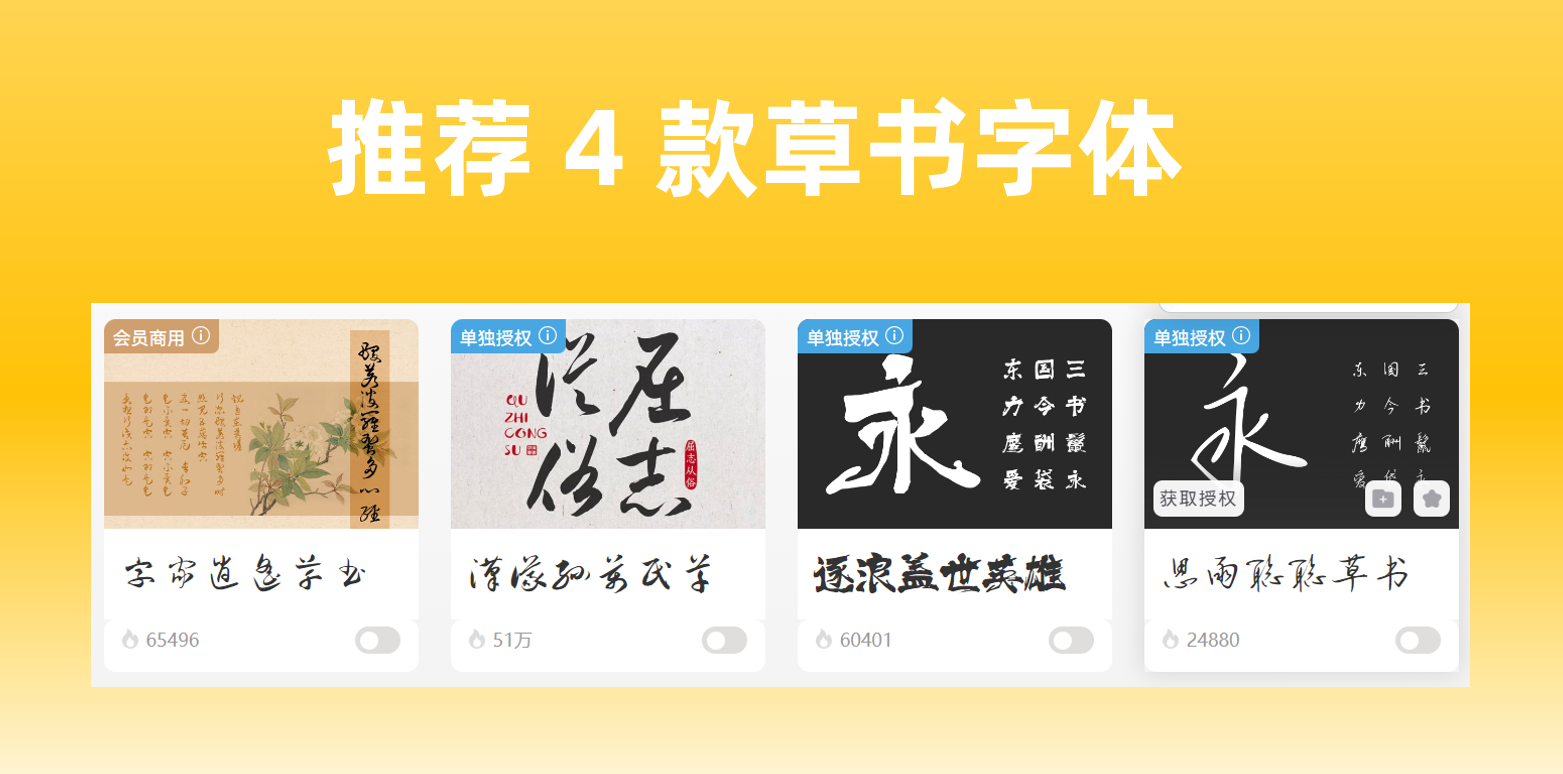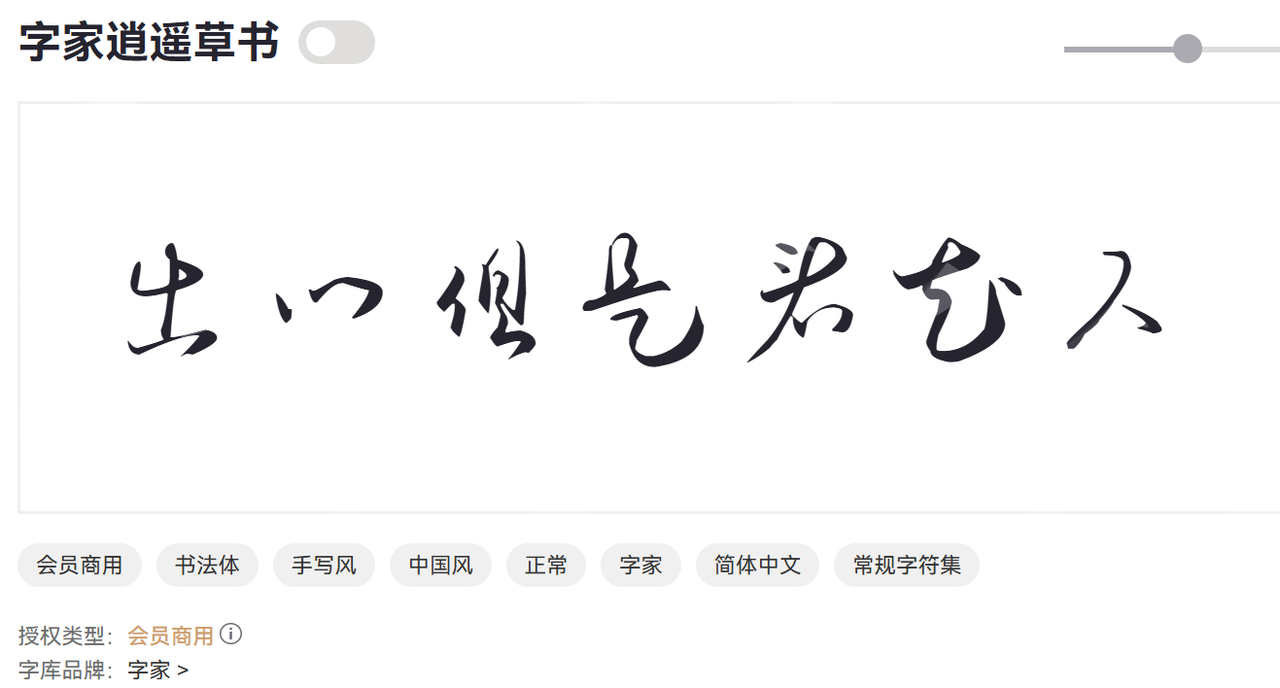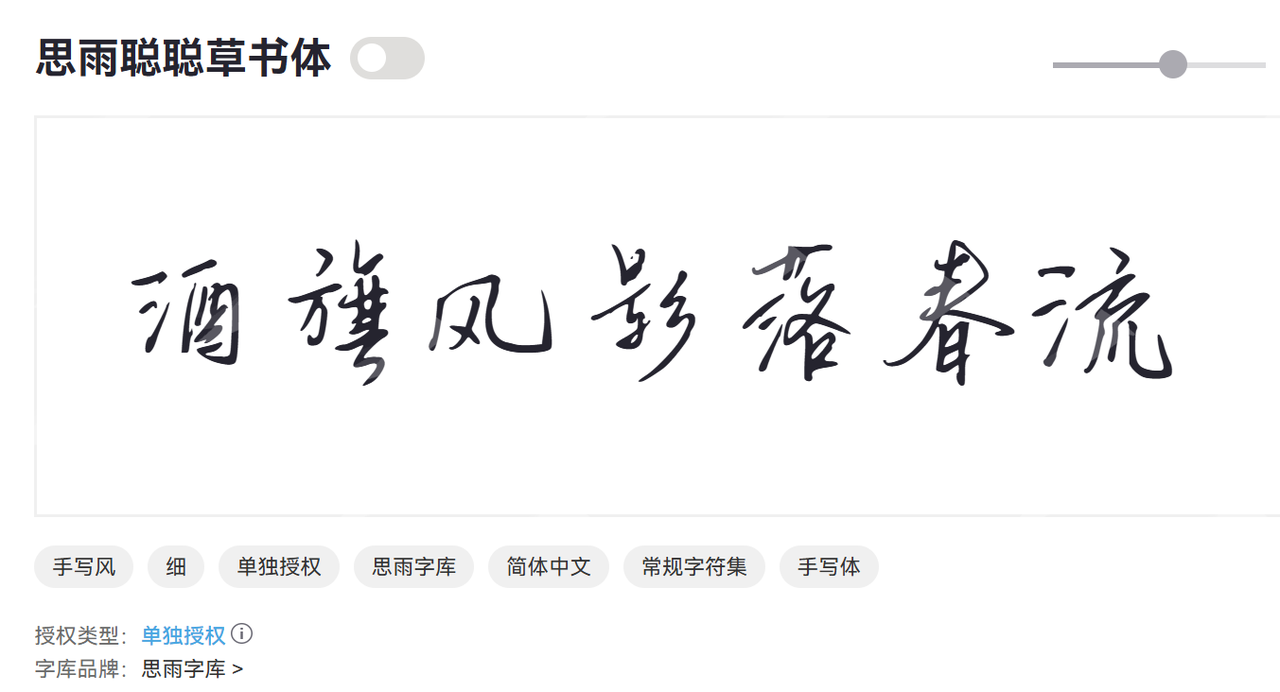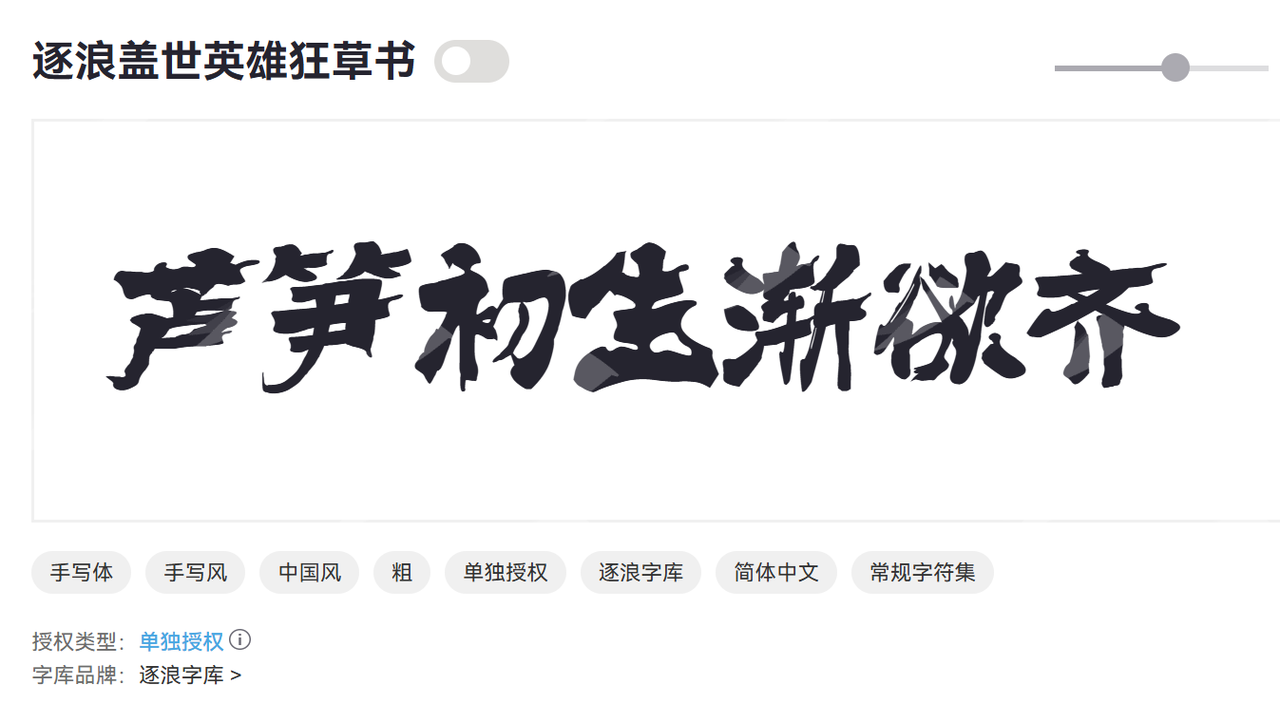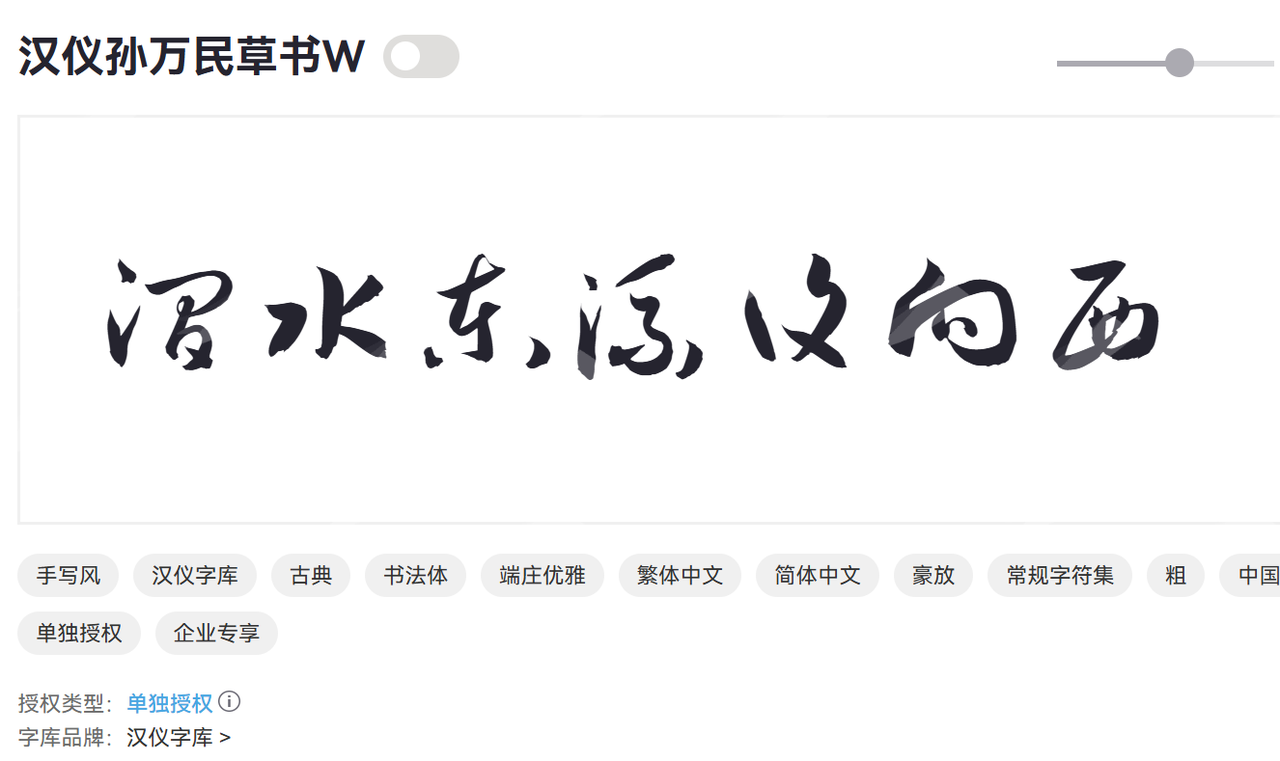
草书字体是否可以商用?推荐 4 款草书字体
提到草书,是不是你会想到王羲之的书法写作,它不仅仅是一种书写方式,更是一种视觉艺术的字体。那么草书字体到底是什么样的字体?我们又该如何在各种场景下使用它?尤其是在商业项目中,草书字体是否可以随意商用!今天就给大家逐一展开,并且给大家重点介绍 4 款商用的草书字体。
1. 草书字体是什么字体?
草书是中国汉字的一种书体,与篆书、隶书、楷书、行书并称为中国书法的五大书体。它的特点是笔画连绵、结构简约、书写速度快,并且富有极强的艺术表现力。
随着科技的发展,传统的草书书法也被设计师们转化成了数字字体。将富有生命力的手写草书转化为可编辑、可输入的数字字体,是一个复杂而精细的过程。设计师需要捕捉草书的精髓,平衡艺术性和实用性,让它们既能保留草书的韵味,又能满足现代设计的要求。因此,我们今天所说的“草书字体”,通常是指那些以草书风格为基础,经过数字化处理后,可以在电脑或手机上直接使用的字体文件。
3. 4 款商用的草书字体
字家逍遥草书
字家逍遥草书是一款充满东方韵味与自由气息的中文草书字体。它汲取了传统草书的精髓,将书法艺术的挥洒自如融入现代设计之中,呈现出一种既古典又富有生命力的独特风格。这款字体以其“逍遥”之名,寓意着笔墨之间无拘无束、超然物外的艺术境界。
字家逍遥草书笔画连贯流畅,如行云流水般自然,充满动感与节奏感。可用于电影片头、书籍封面、产品包装、文创周边、个性化签名等多种设计应用,为您的项目增添独特的艺术魅力。
思雨聪聪草书体
思雨聪聪草书体是一款融合了传统草书的灵动与现代审美的中文艺术字体。它以其独特的笔触和富有个性的设计,展现出一种清新、活泼而不失雅致的风格。
思雨聪聪草书体笔画轻盈且富有弹性,连笔自然,整体呈现出一种活泼的流动感。 适用于标题、宣传语、海报设计、个性化签名、社交媒体配图等多种场景,在实际的工作中,我经常用在一些文艺、小清新的设计风格。
逐浪盖世英雄狂草书
逐浪盖世英雄狂草书是一款气势磅礴、笔势狂放不羁的中文狂草字体。它将中国书法中“狂草”的精髓发挥到极致,每一个字都如同波涛汹涌的巨浪,蕴含着英雄般的豪迈与力量。
逐浪盖世英雄狂草书笔画大开大合,连绵不绝,整体视觉效果极其震撼,充满雄伟之气。在各类标题、标志、广告语中运用,能瞬间提升信息的权威感和艺术感染力,大家可以在 banner 的标题中尝试使用一下这个字体。
汉仪孙万民草书
汉仪孙万民草书是一款由知名字体厂商汉仪字库出品,它秉承了传统草书的典雅与流畅,同时融入了现代字库制作的严谨与规范,使其在保持艺术性的同时,具备了高度的实用性和专业性。
汉仪孙万民草书笔画连贯自然,整体风格端庄而不失灵动,兼具传统韵味与现代美感。无论用于书籍装帧、企业VI、海报宣传,都能显著提升设计的整体档次和艺术气息。
4. 草书字体的使用场景
草书字体因其独特的艺术魅力,在很多场景下都能发挥出惊艳的效果。
- 品牌Logo与名称: 草书的个性化和艺术感使其非常适合作为品牌Logo或产品名称。例如,高端茶品、白酒、文化创意产品、艺术机构、传统服饰品牌等,使用草书Logo能迅速提升品牌的文化品味和辨识度,营造出一种东方韵味或古典雅致的氛围。
- 艺术品与展览: 艺术品说明和展览海报的标题,我们在生活场景中是比较常见的。
- 文化类出版物封面: 诗集、古籍、历史文献、书法教程、国学读物等书籍的封面,使用草书字体能强化其文化属性和艺术气息,吸引目标读者。
- 高端餐饮与酒店: 餐厅的招牌、菜单设计、酒店的指示牌或宣传语。
- 传统节庆与活动: 春节对联、中秋贺卡、婚礼请柬、文化节庆活动的宣传海报,尤其是春联,我家里经常自己写对联,就是用草书写的。
不适合草书字体的场景:
- 大段正文阅读: 草书的可读性较低,不适合作为报纸、杂志、网页或书籍的正文,会导致读者阅读疲劳,难以理解。所以不建议大家在正文中使用。
- 需要快速识别的场景: 交通指示牌、紧急通知、安全警示等,需要人们在短时间内快速获取信息的场合,这一类场景需要快速识别信息,所以不要使用草书。
- 现代科技感强烈的项目: 如果你的设计项目追求的是极简、科技、未来感,那么过于传统和艺术化的草书字体可能会显得格格不入。
- 儿童读物或面向大众的普及性内容: 对于儿童或文化背景较少的人群,草书可能过于抽象,难以理解。